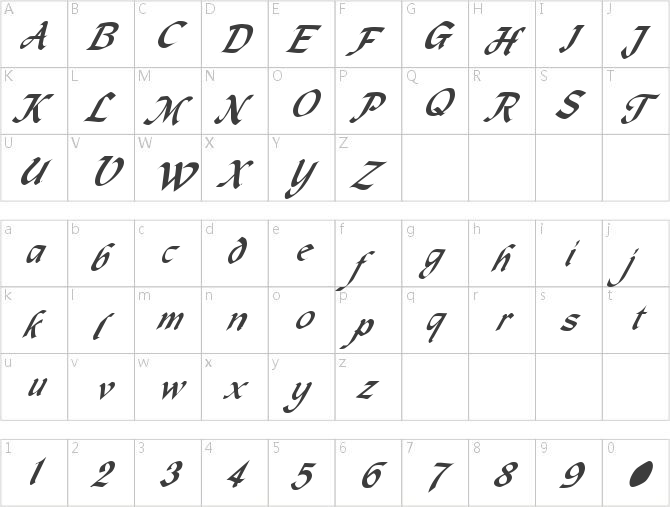
Metermiser-Italic 詳情頁(yè)
Metermiser-Italic字體字庫(kù)是一款讓人賞心悅目、百看不厭的英文字體,適合各類廣告和產(chǎn)品包裝設(shè)計(jì)應(yīng)用,字體大小0.03MB,格式為ttf字體,上傳用戶是志誠(chéng)設(shè)計(jì),作者/版權(quán)方為未知